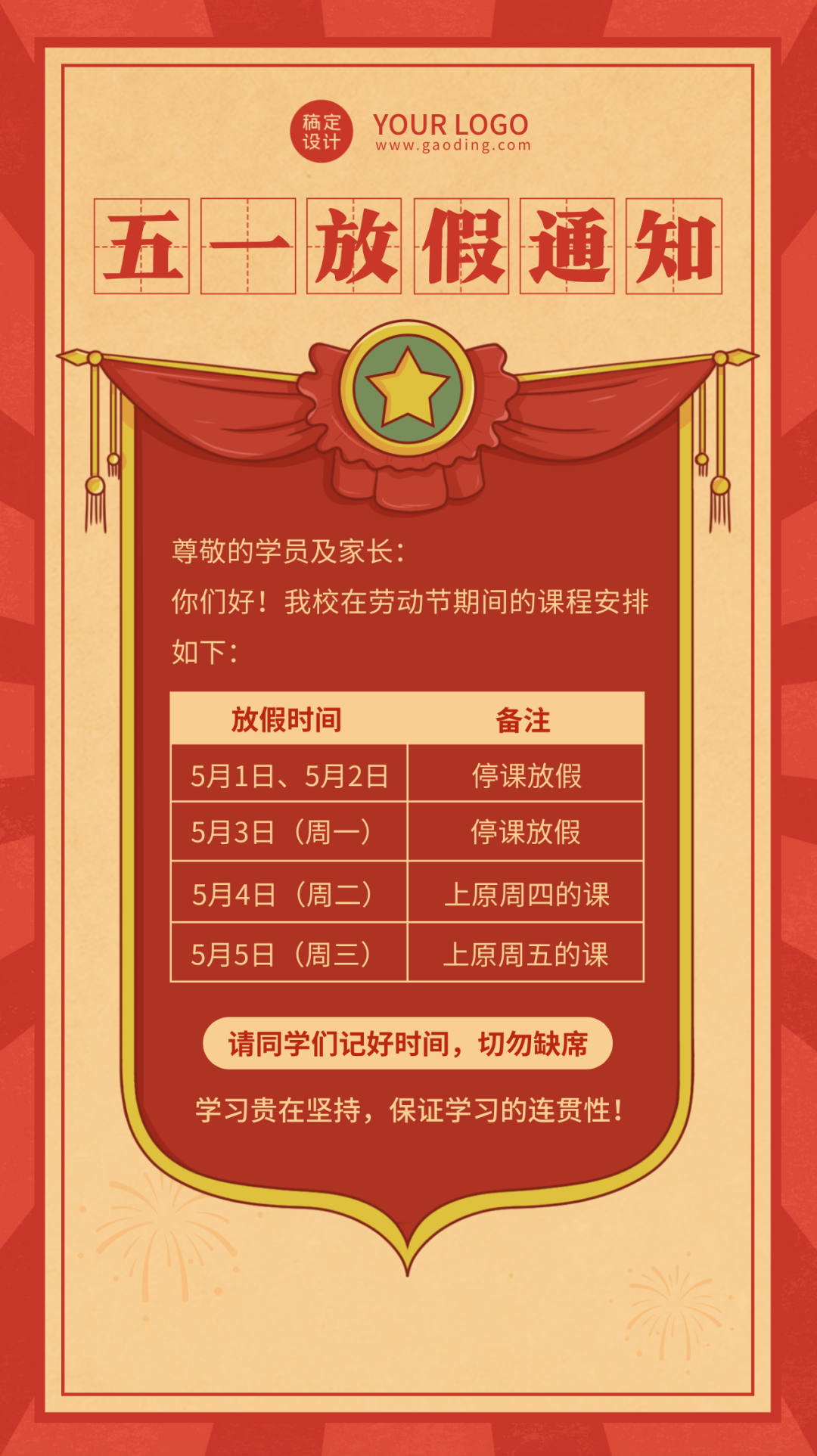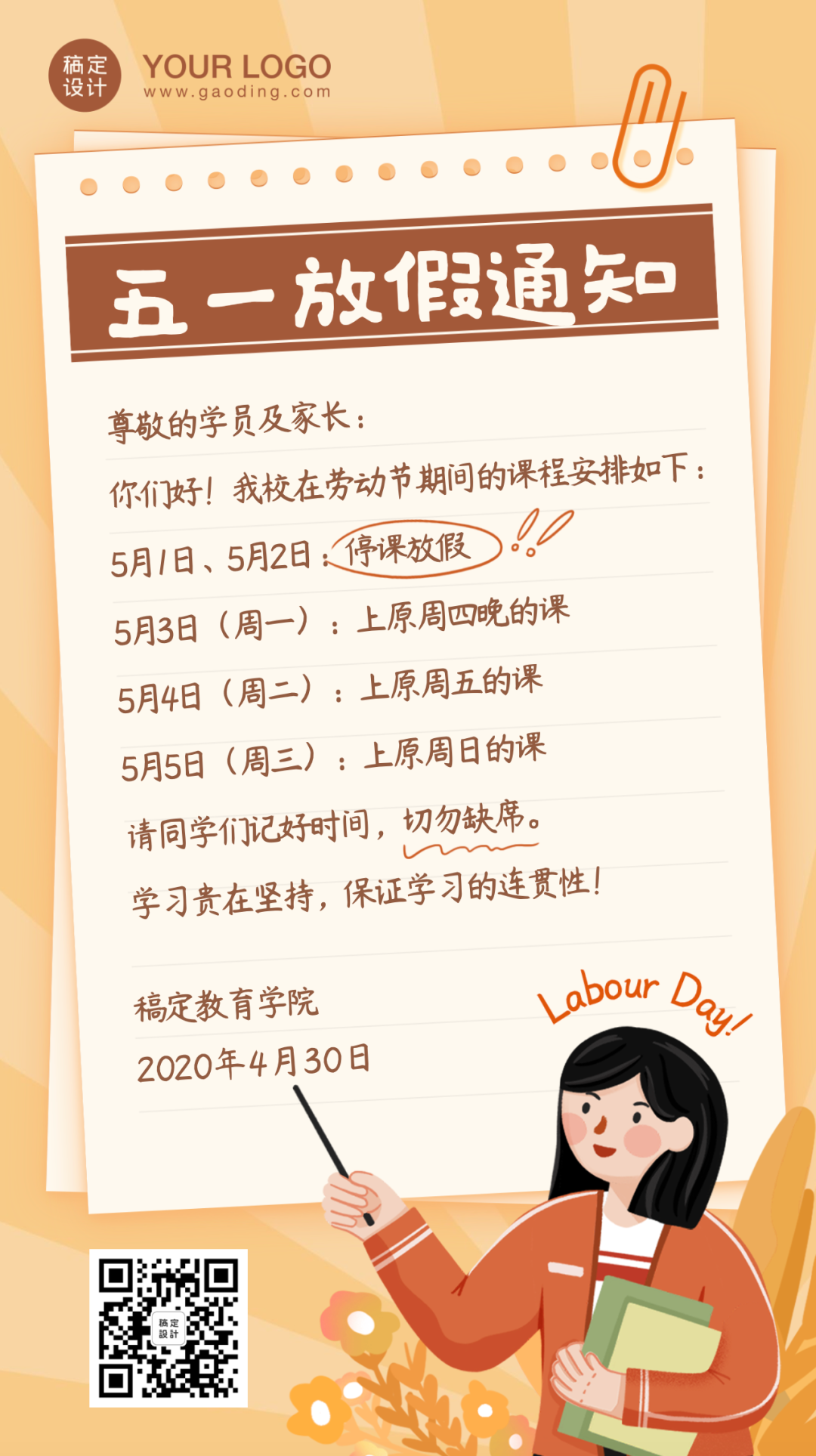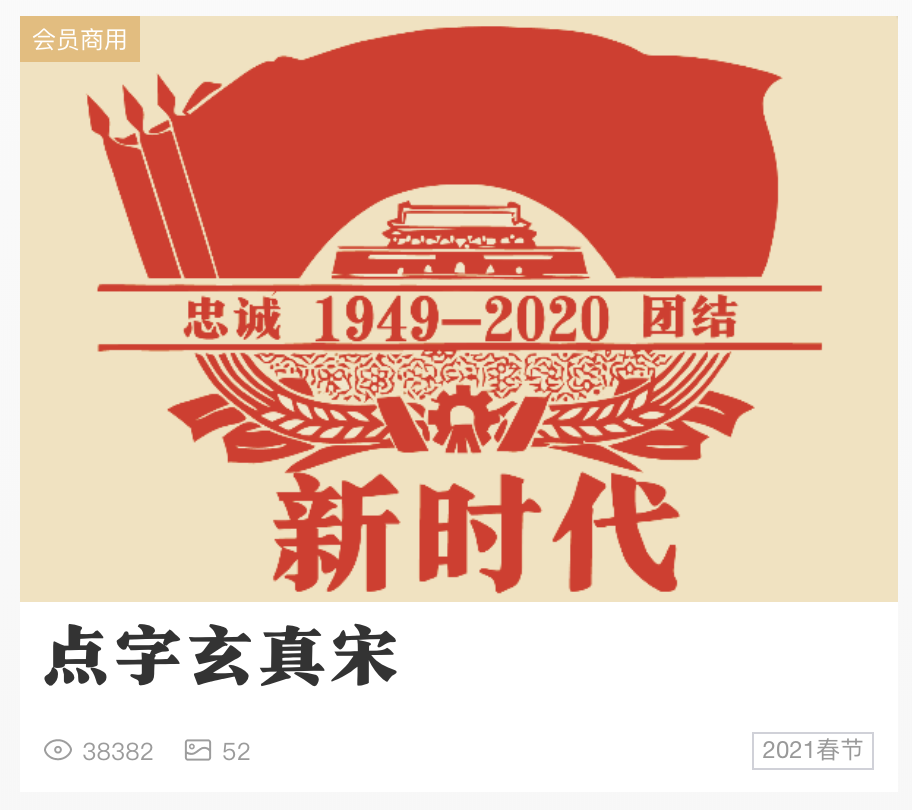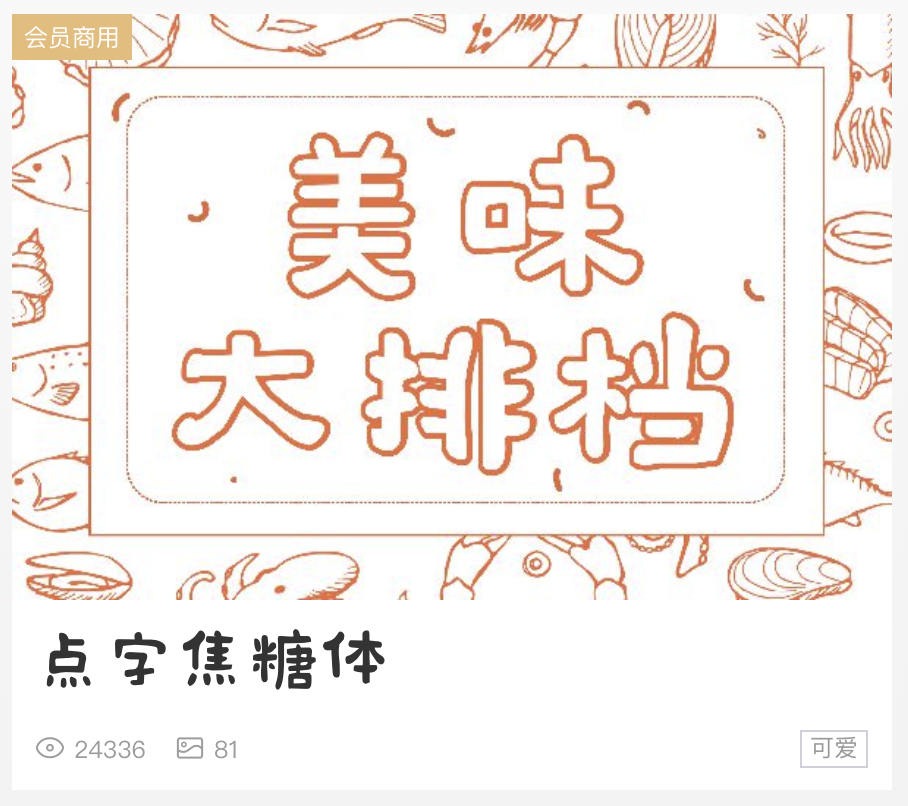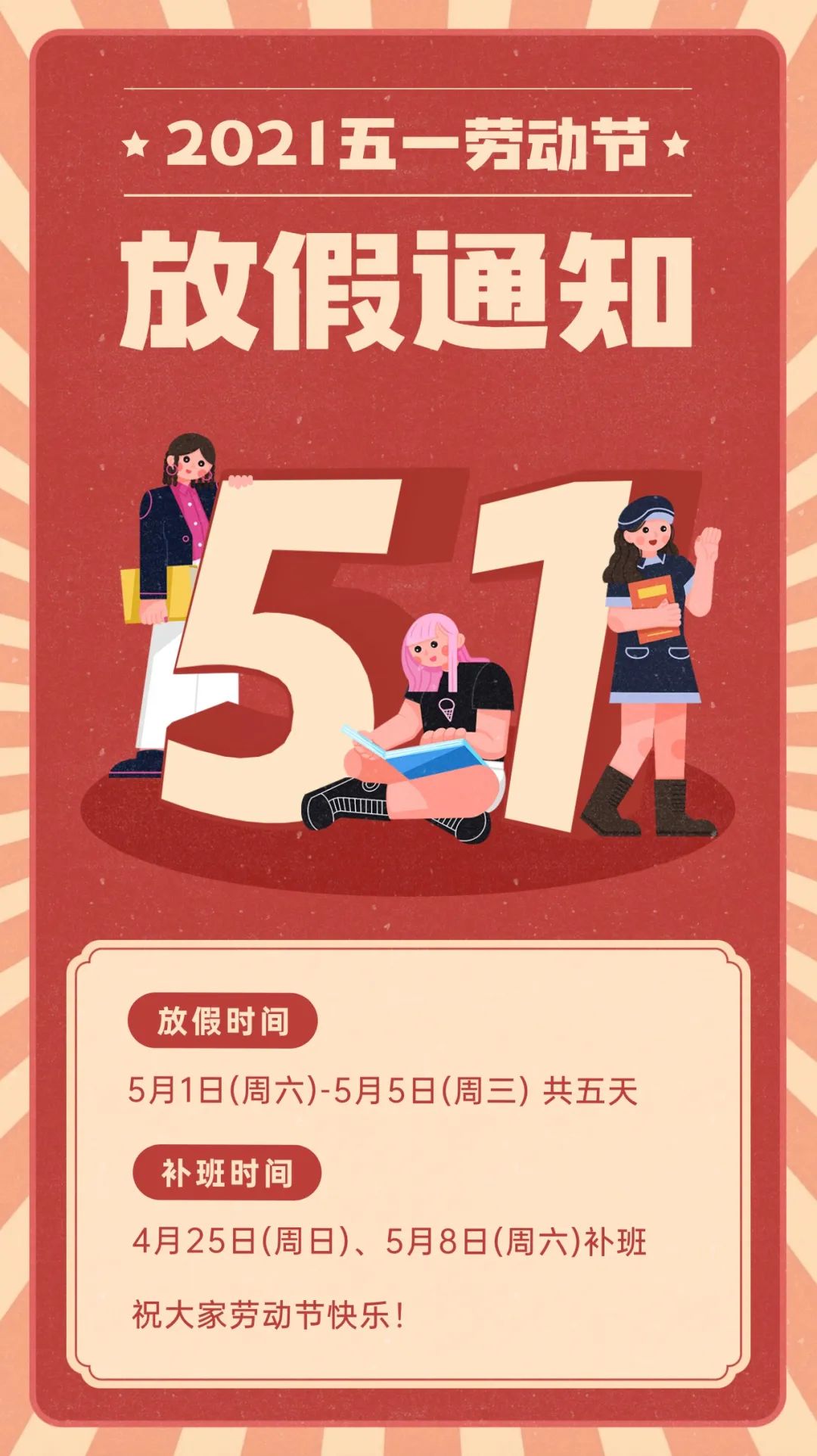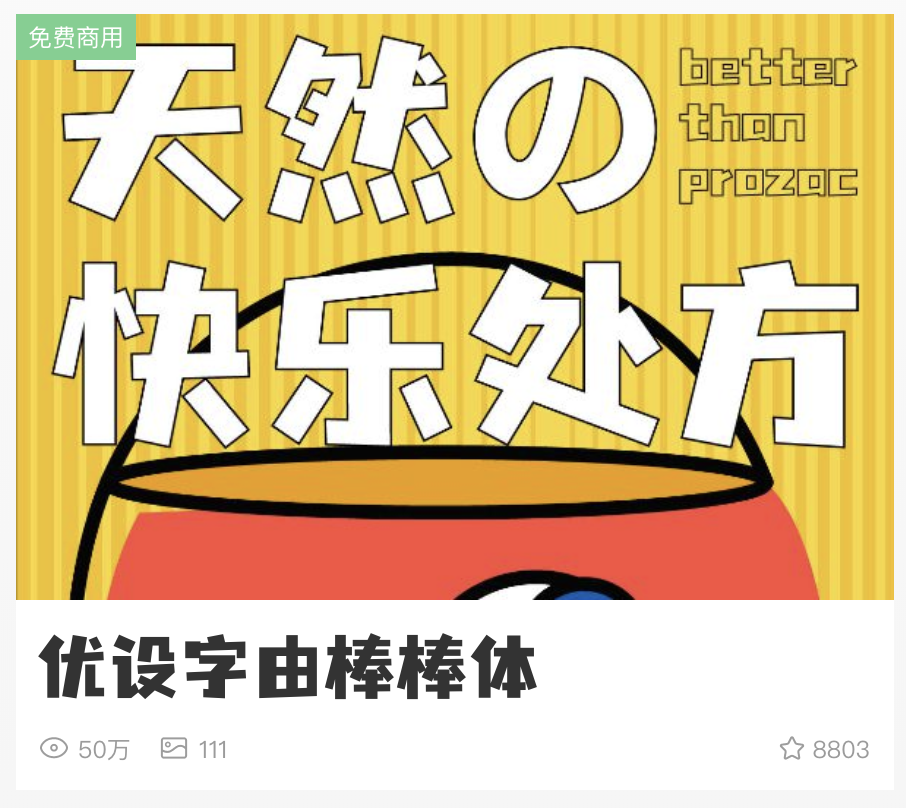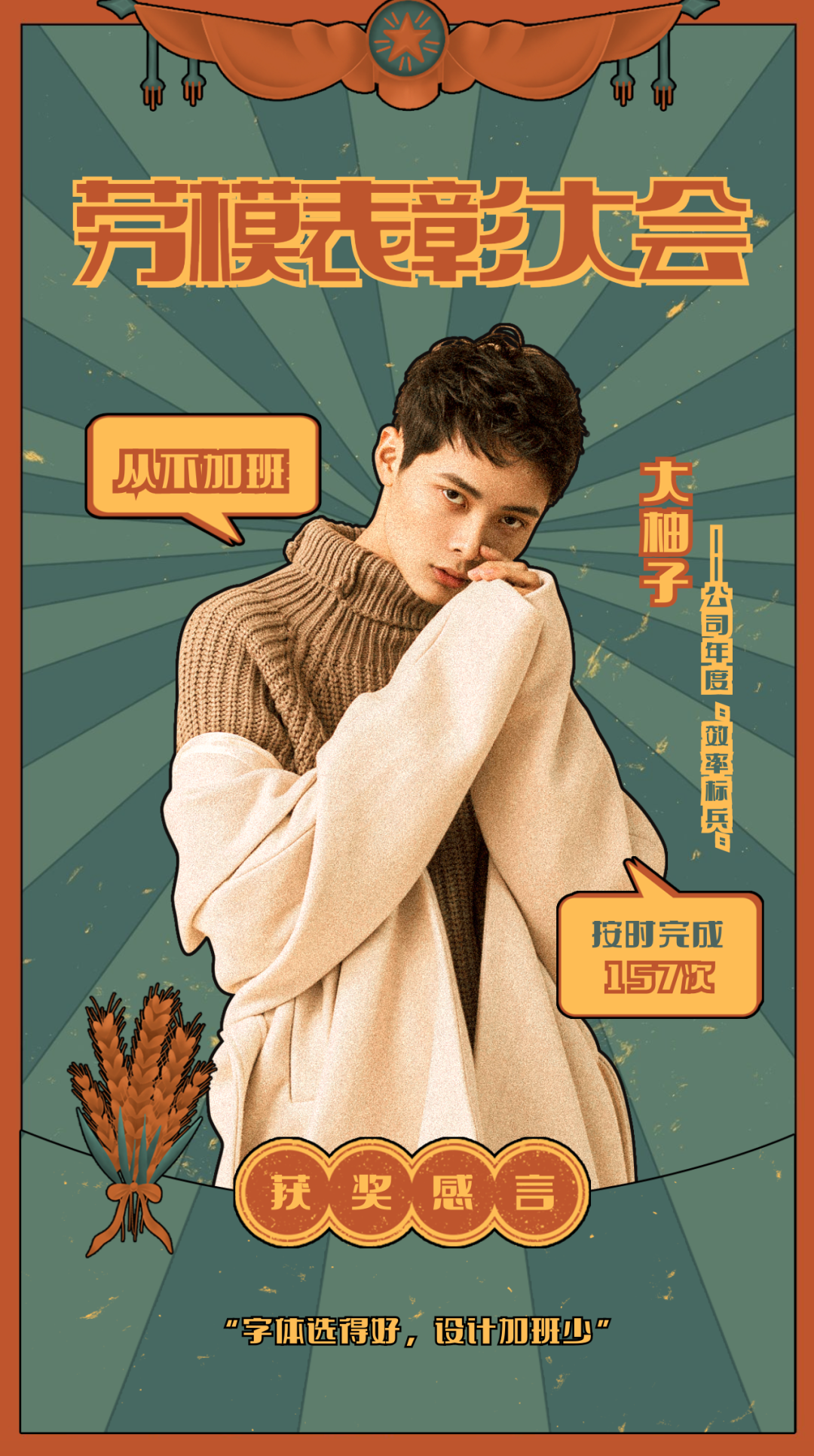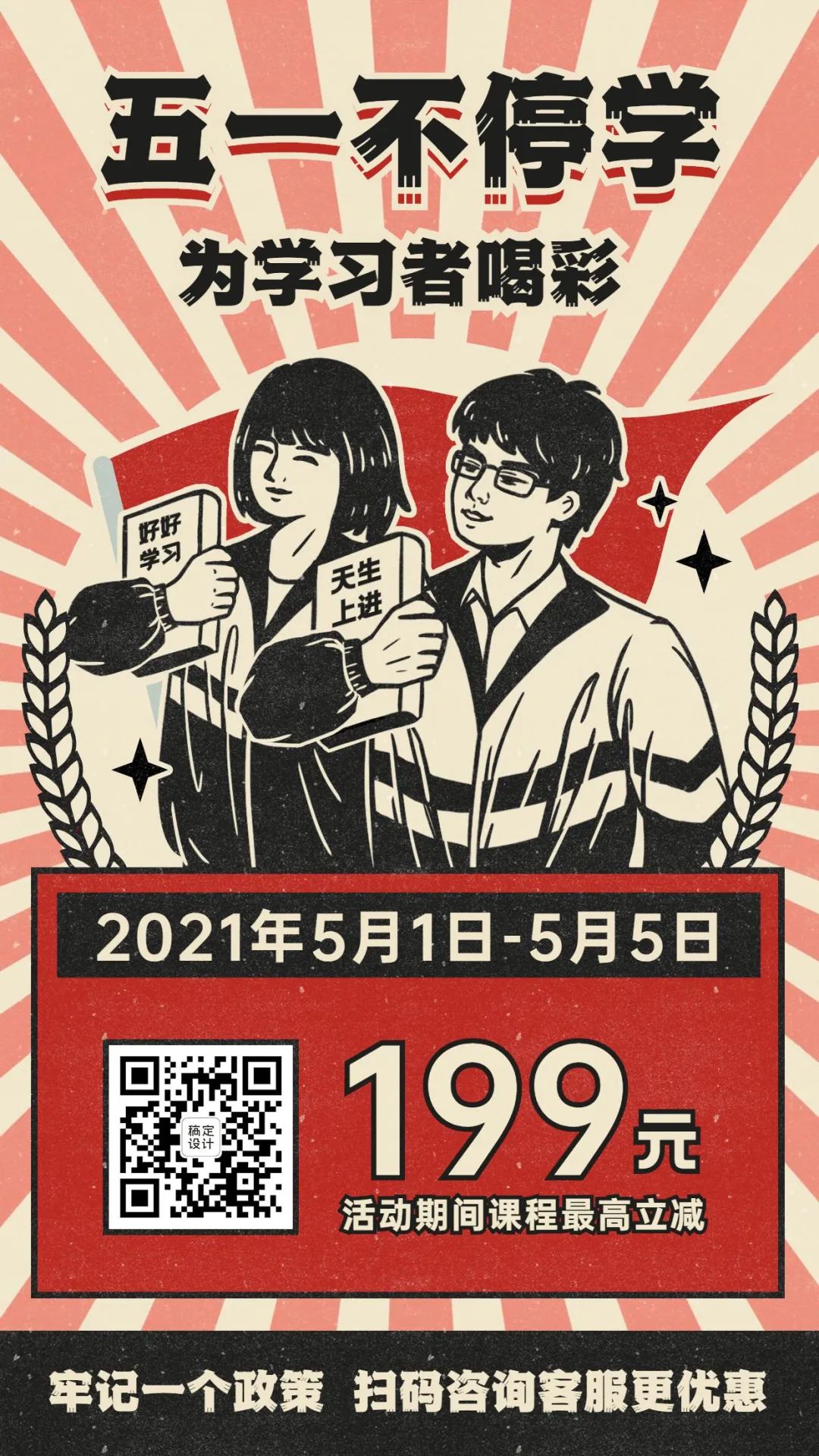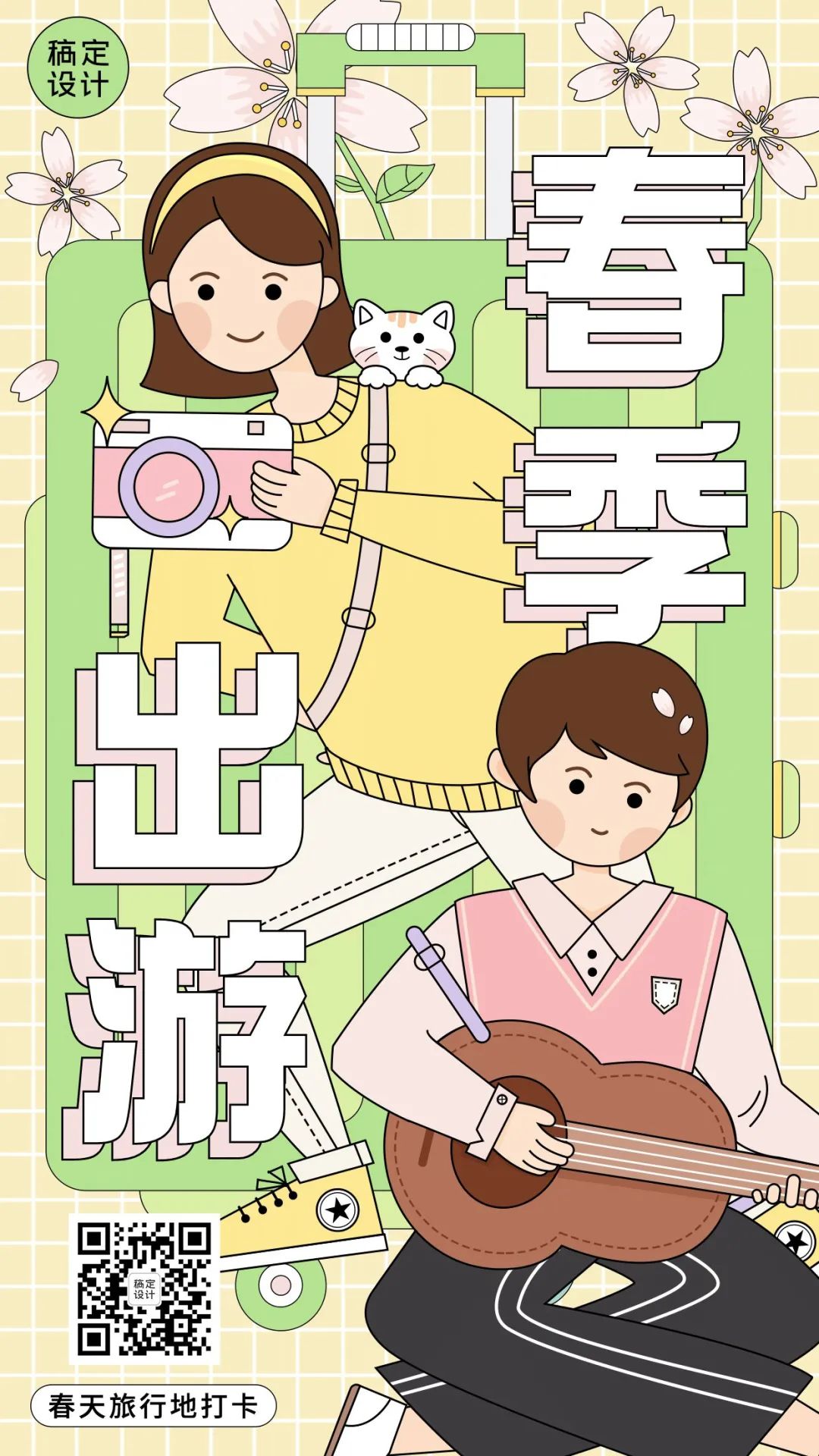
不想加班的设计师都是这么做的!
前两天的热搜看得柚子咬牙切齿。出来工作都不易,只要你上班,我们就是好兄弟,本是同根生相煎何太急?
一个年轻人到底要经历多少,才能成为一名成熟的劳动者?
年轻的设计师,加班,你怕了吗?
我不怕!因为属于我的节日马上就要来啦!虽然可能还要做一张劳动节海报,但有了字由,这些都是小菜一碟~
当然,设计师会用更专业的软件,为此柚子贴心准备了干劲满满的五一字体!海报早做完早放假!😊
也许你需要用点字玄真宋做一张根正苗红的放假通知?
或者用点字焦糖体做一张可爱风格的停课通知。
而点字墩墩体,最适合创意十足的互联网公司了。
劳动节大都想犒劳自己一下,买买买不停。这时电商就要抓住机会搞促销,免费可商用的字由文艺黑绝不能错过。
同样大火的免费可商用字体优设字由棒棒体当然也要出来亮个相~老板给我放假,我给老板省钱✌️
像柚子这么为公司着想的设计师,也该被老板表彰一下了(疯狂暗示)
当然也有自律性超强的小伙伴在好不容易得来的五一假期里选择提升自己,好好学习!你们就是最强的!
提升自己的同时也不要忘了陪陪家人~劳动节过后紧接着就是母亲节,全家踏青安排上。
不管去哪儿玩,带上愉快心情的同时,也不要忘记戴上口罩哦😳
最后用无敌的点字永胜粗宋提前祝大家节日快乐啦~
劳动最光荣~劳动人民无所畏惧,永胜无敌!